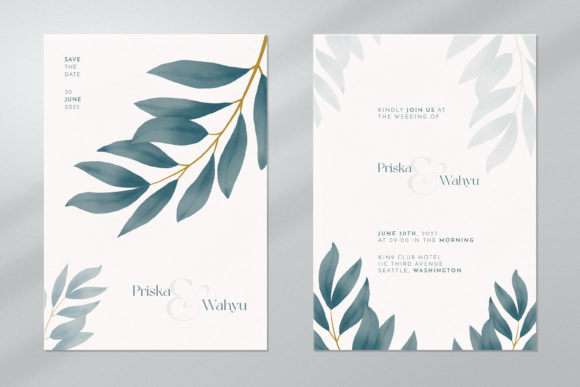
Watercolor Flowers Wedding Invitation
Ulasan: Watercolor Flowers Wedding Invitation – Elegância em Cada Detalhe
Se você está procurando o convite perfeito que combine delicadeza, sofisticação e praticidade, o Watercolor Flowers Wedding Invitation chega como a escolha ideal. Ideal para casamentos, aniversários ou festas especiais, este modelo traz um toque artístico que encanta à primeira vista. Descubra neste review por que ele tem conquistado noivos, designers e organizadores de eventos.
Por que escolher este convite?
- Design exclusivo em aquarela – As flores pintadas à mão criam um visual romântico e atemporal, perfeito para cerimônias ao ar livre ou cerimônias formais.
- Tipografia elegante – Combinação das fontes NewYork (para títulos) e Josefin Sans (para corpo de texto), proporcionando leitura clara e estilo contemporâneo.
Experiência de personalização
Qualidade de impressão